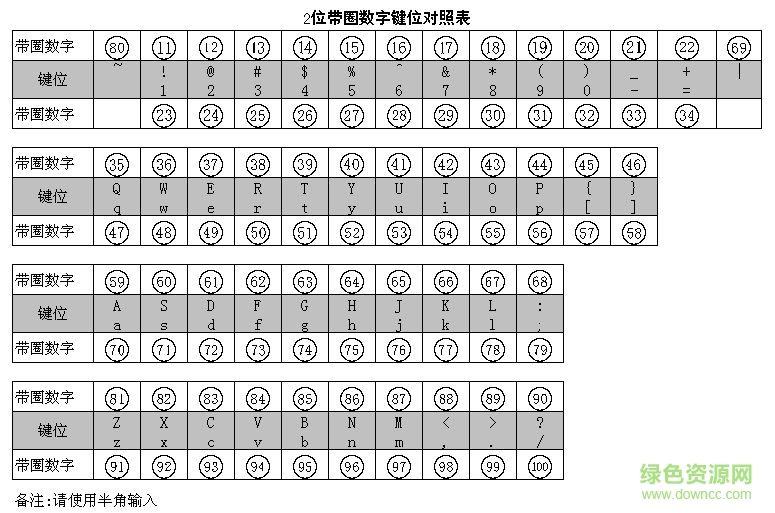
cnumber2.ttf字體是一款獨特的帶圈圈數(shù)字字體,輸入兩位數(shù)字可自動帶圈,在辦公中經(jīng)常用到,安裝方法也非常簡單,需要的朋友歡迎在綠色資源網(wǎng)下載!
"CNumber2.ttf"文件是數(shù)字11到100的帶圈數(shù)字的字體文件。其安裝方法同其它字體一樣,最簡單的方法就是把"CNumber2.ttf"文件復制到字體文件夾(控制面板——字體)中即可。使用方法也同其它字體一樣!